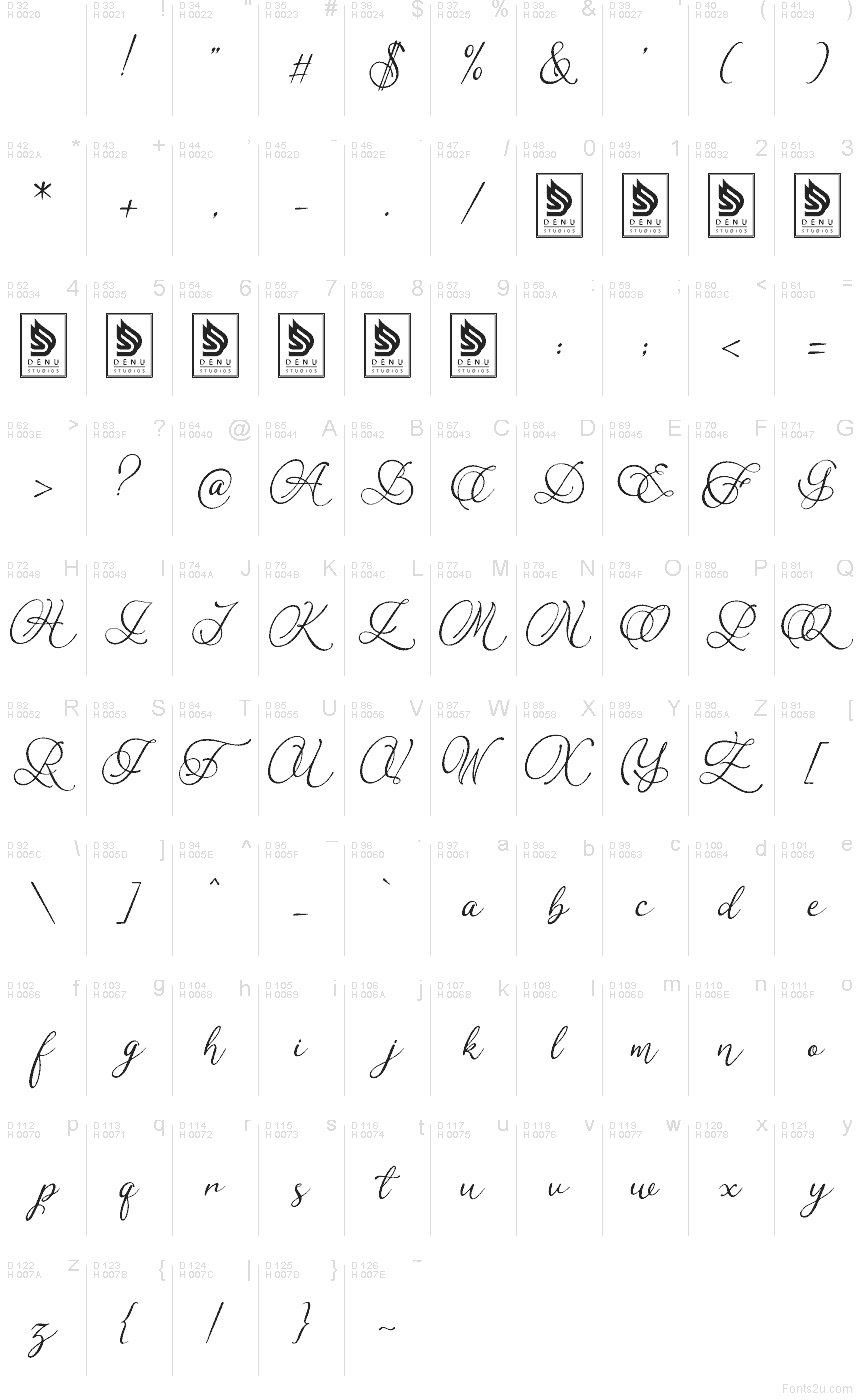
Aespa Maribell von Denustudios ist eine kostenlose, romantische Kalligrafie-Schrift mit langen, geschwungenen Linien und einer leichten, handgezeichneten Anmutung. Die Buchstaben bestechen durch luftige Verzierungen und feine Linienführungen, was der Schrift einen eleganten, dekorativen Rhythmus verleiht – beinahe wie eine handgeschriebene Einladung und weniger wie eine alltägliche Schreibschrift.
Sie passt perfekt auf Hochzeitspapeterie, in das Branding für Kosmetikprodukte, Parfümverpackungen, Cover-Designs oder Titelgrafiken, bei denen eine kostenlose Schrift einen sanften, hochwertigen Mode-Look vermitteln soll. Verwenden Sie sie immer dann, wenn Namen, kurze Überschriften, Monogramme oder Logos im Signatur-Stil fließend und etwas theatralisch wirken sollen, denn die ausladenden Schwünge sorgen bereits für eine beeindruckende visuelle Wirkung.